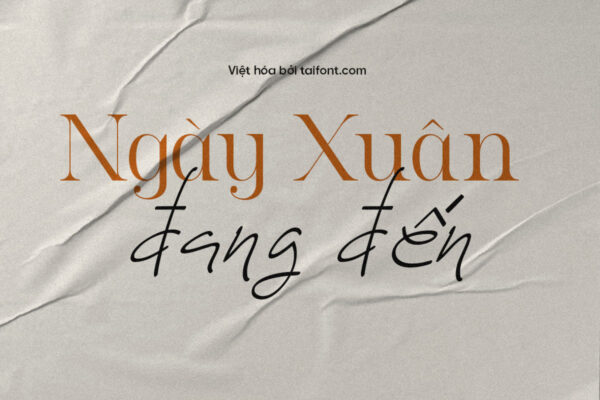
Giới thiệu Combo Font TF Roze Belinda Regular & Script Việt hóa
Bộ đôi TF Roze Belinda Regular & Script Việt hóa là sự kết hợp hoàn hảo giữa nét hiện đại, sang trọng và sự mềm mại, lãng mạn. Đây là lựa chọn lý tưởng cho các nhà thiết kế muốn tạo ra những ấn phẩm tinh tế, đa dạng phong cách mà vẫn giữ được sự đồng bộ.
1. TF Roze Belinda Regular Việt hóa: Là font chữ có chân (serif) với vẻ đẹp hiện đại và sang trọng. Những đường nét được trau chuốt tỉ mỉ, cùng với các glyphs (ký tự đặc biệt) thú vị, mang đến sự thanh lịch, chuyên nghiệp. Font này phù hợp cho:
- Thiết kế logo, tiêu đề chính: Tạo điểm nhấn mạnh mẽ, đẳng cấp cho thương hiệu.
- In ấn, tạp chí, thời trang: Đảm bảo tính thẩm mỹ cao và sự rõ ràng trong các ấn phẩm.
2. TF Roze Belinda Script Việt hóa: Là phiên bản font viết tay (script font) bay bổng, mềm mại và đầy lãng mạn. Với nét chữ uyển chuyển như viết bằng tay, font này tạo cảm giác cá nhân hóa và sự tinh tế.
Sức mạnh của Combo:
Khi kết hợp, TF Roze Belinda Regular và Script tạo nên một cặp đôi hoàn hảo:
- Roze Belinda Regular lý tưởng cho các phần tiêu đề, tên thương hiệu, mang lại sự rõ ràng và đẳng cấp.
- Roze Belinda Script sẽ làm điểm nhấn cho các lời tựa, chữ ký, hoặc đoạn văn bản phụ cần sự mềm mại, lãng mạn trên thiệp mời, thiệp cưới, hoặc các ấn phẩm thời trang.
Sự tương phản nhưng vẫn hài hòa giữa hai font giúp bạn tạo ra những thiết kế có chiều sâu, đa dạng phong cách, từ trang trọng đến lãng mạn, mang lại vẻ đẹp độc đáo và chuyên nghiệp cho mọi dự án.
Font Việt hóa TF Roze Belinda Regular và Script